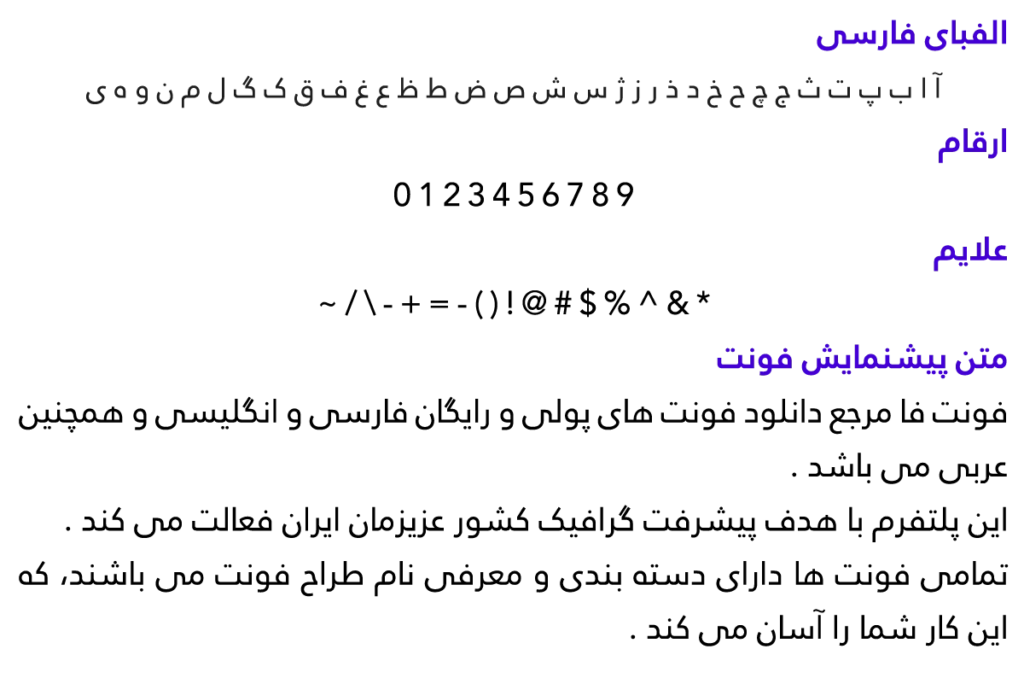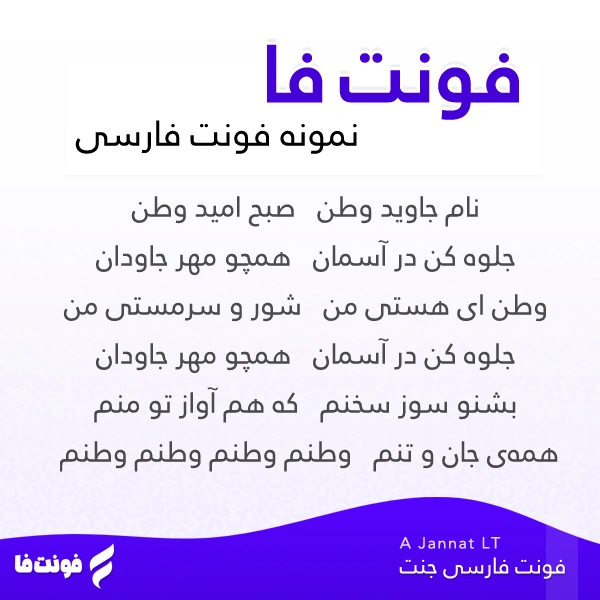
فونت فارسی جنت – A Jannat LT
سال ساخت فونت: 1387
نوع فونت: فونت عنوان و فونت متن
توضیحات و معرفی فونت جنت
فونت فارسی جنت ( A Jannat LT ) از مجموعه فونت های آزاد می باشد، و نیز نوع فونت عنوان و متن می باشد.
فونت خوشگل مربوط در سال 1387 طراحی و ساخته شده است، که از این فونت در طراحی لوگو یاهو استفاده شده است.
لیست وزن و فرمت های فونت A Jannat LT
و نیز فونت A Jannat LT در 2 وزن پر رنگ و معمولی است.
در لیست زیر می توانید وزن های این فونت خوشگل را ببینید.
- A Jannat LT Bold
- A Jannat LT Regular
در تصویر زیر می توانید شعر زیبای «وطنم» را که با این قلم نوشته شده، تماشا کنید.